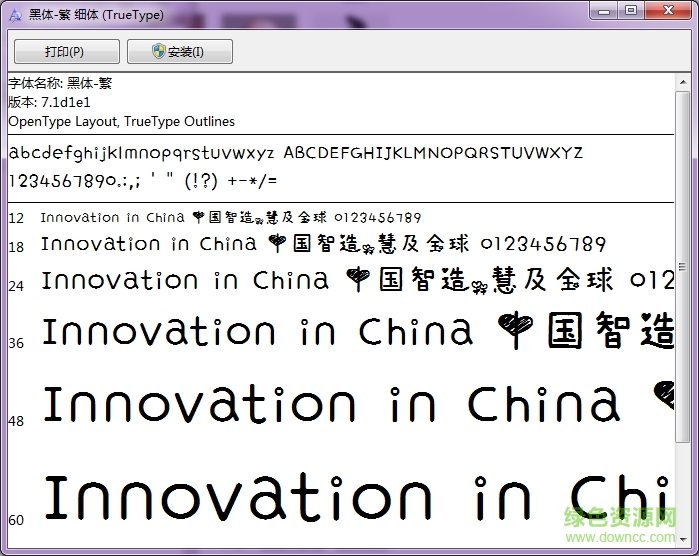
小兔闹革命字体是一款十分俏皮的艺术字体,字体行间充满了多种可爱的点缀,给人童真童趣的视觉好看,本字体造型别致、有独特的艺术美感,喜欢收藏的朋友千万不要错过啦,来绿色资源网领取吧!
小兔闹革命字体是一款用于可爱创意设计方面的字体,字体十分俏皮搞怪,字体设计感十足,可广泛运用于艺术设计、海报设计、排版印刷等多种场合。